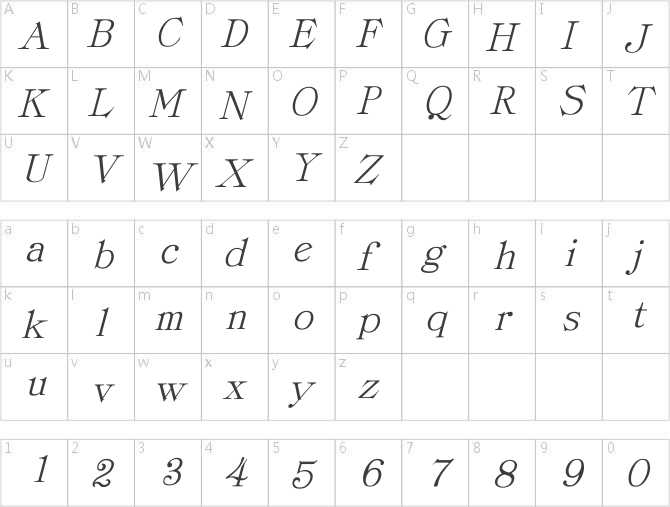
ProvLite-Italic 詳情頁
ProvLite-Italic字體字庫(kù)是一款讓人賞心悅目、百看不厭的英文字體,適合各類廣告和產(chǎn)品包裝設(shè)計(jì)應(yīng)用,字體大小0.13MB,格式為ttf字體,上傳用戶是1733150348,作者/版權(quán)方為未知